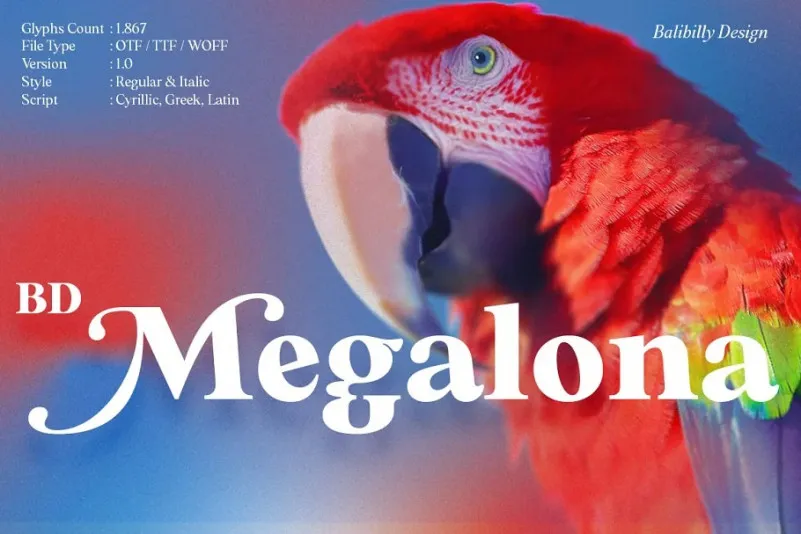
A BD Megalona Font é uma elegante fonte serif que oferece um equilíbrio perfeito entre curvas e linhas retas, criada pelo designer Balibilly Design através de uma abordagem meticulosa e perseverança. Esta fonte vem em versões maiúsculas e minúsculas, com linhas arredondadas e elegantes que se sobressai no mercado das fontes serif. Sua característica mais destacável é seu extenso conjunto de caracteres, contendo aproximadamente 1800 gílios. Esta quantidade impressionante de caracteres abrange ao menos 219 línguas, incluindo as alfabetizações latinas e gregas, além das alphabéticas cílindrica (fundamental e extensivo). Com uma série de recursos avançados em open type disponíveis como alternativas estilísticas, formas terminais, swashes, ligaturas discretionary, ordinais, minúsculas posicionadas, frações e forma sensível ao caixa. BD Megalona Font é ideal para projetos que valorizam uma fonte sofisticada com um toque de personalidade. A sua versão extensa de caracteres permite-lhe explorar novas possibilidades criativas sem se preocupar em cortar qualquer letra, e o conjunto completo de recursos open type a torna perfeita para designers exigentes.